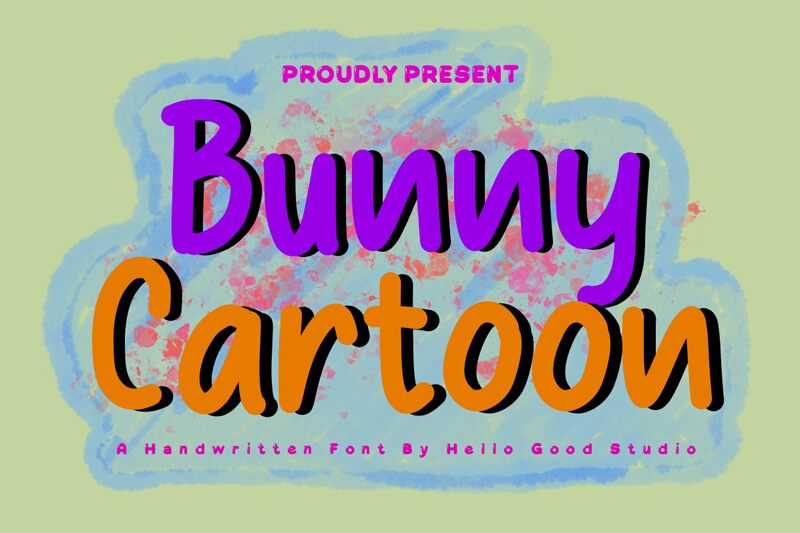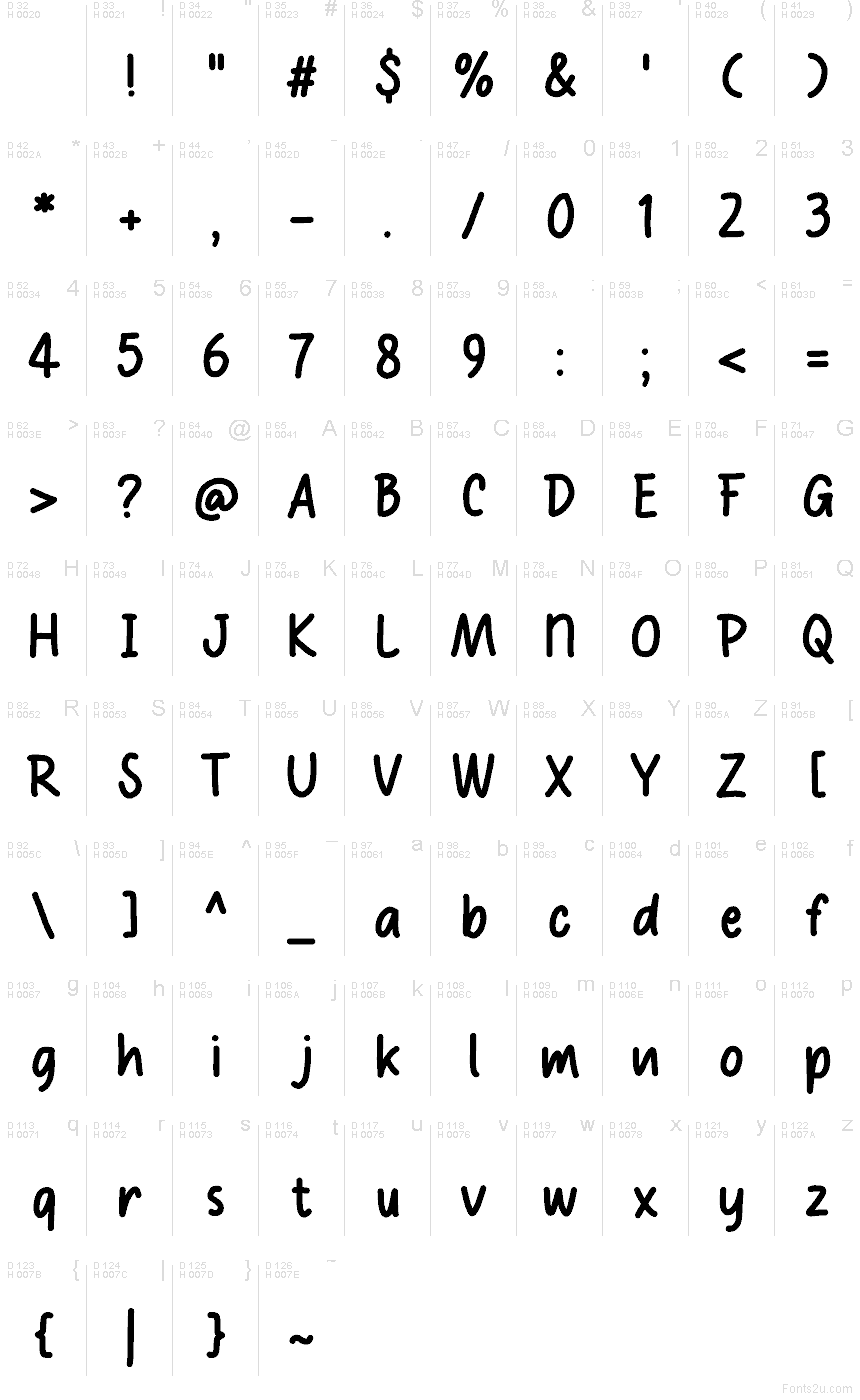
Bunny Cartoon od Hello Good Studio to darmowy, odręczny krój pisma w stylu rysunkowym, charakteryzujący się miękkim, skocznym rytmem oraz grubymi, pędzlowymi literami. Zaokrąglone kreski i lekko nierówne łączenia nadają mu zabawny, nieformalny charakter, kojarzący się raczej z energią sympatycznej maskotki niż z wygładzonym pismem odręcznym.
Świetnie sprawdzi się na okładkach książek dla dzieci, opakowaniach przekąsek, zaproszeniach urodzinowych, miniaturach na YouTube czy w radosnych projektach logo – wszędzie tam, gdzie darmowy font musi emanować ciepłem i bezpośredniością. Wykorzystaj go w krótkich nagłówkach, na naklejkach, etykietach z imionami czy planszach tytułowych, gdy chcesz, aby litery wyglądały na ręcznie rysowane, w uroczy i celowo lekko niezdarny sposób.